دانلود Sketched, Cartoon & Eroded Fonts 15 فونت انگلیسی با طراحی اسکچ کارتونی
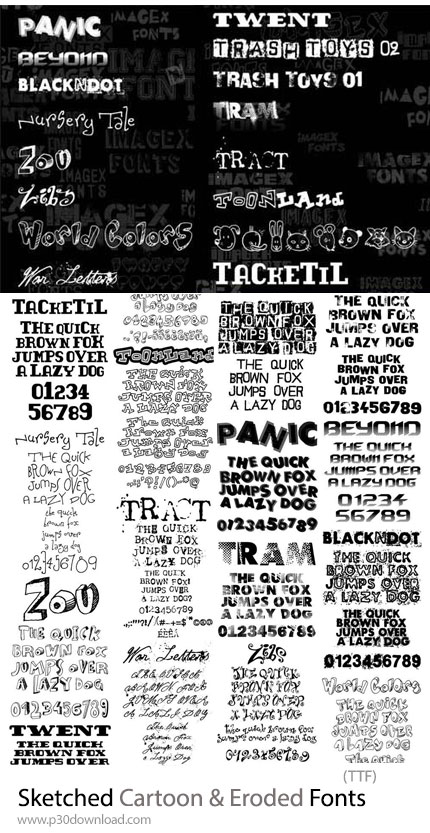
این مجموعه شامل 15 فونت اسکچ دستی کارتونی با جلوه فرسوده است که با الهام از طراحیهای دستی و بافتهای نوستالژیک ساخته شده و با فرمت TTF برای دانلود در سایت قرار گرفته است. این فونتها با ظاهری جذاب و منحصر به فرد، گزینهای ایدهآل برای پروژههایی هستند که به دنبال ایجاد حس خلاقیت، صمیمیت و اصالت میباشند. استفاده از این مجموعه فونتها به شما امکان میدهد تا طرحهای کارتونی، نوستالژیک و جذاب بسازید و هویت بصری منحصر به فردی برای پروژههای خود ایجاد کنید.
ویژگیها و قابلیتها:
- طراحی دستی با بافتهای فرسوده که جلوهای نوستالژیک و کارتونی به پروژه میدهد.
- قابلیت ترکیب با عناصر تصویری و گرافیکی دیگر برای خلق طرحهای منحصر به فرد.
- ایجاد حس صمیمیت و اصالت در پروژهها و کمک به جلب توجه مخاطبان.